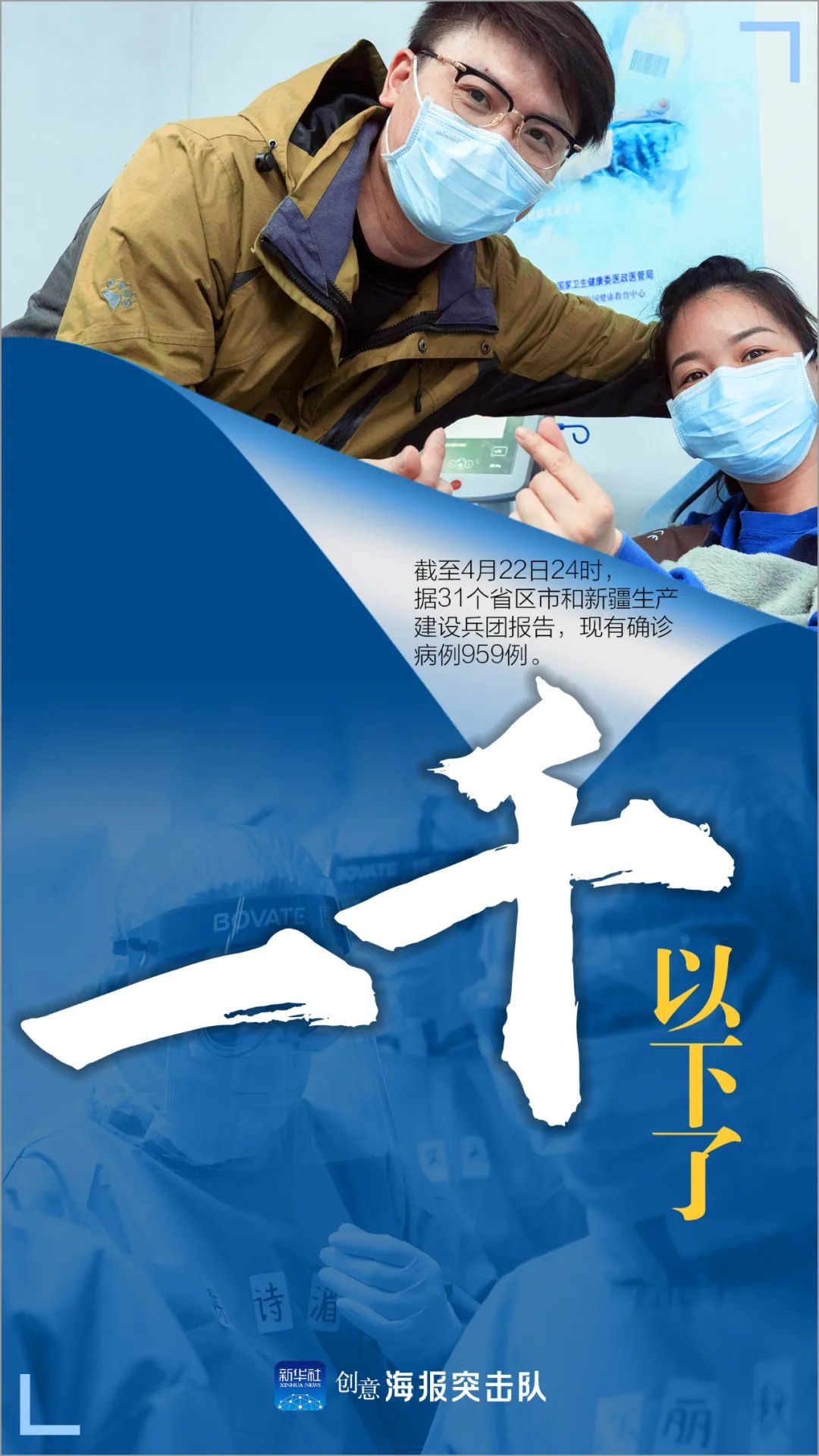
方正清刻本悦宋家族
杨雁
2021年新开发的方正清刻本悦宋有5个不同粗细字重,构成清刻本悦宋家族字体。该字体的设计源于清朝“武英殿”铜活字本《四书章句》。武英殿多以长方宋体字刻印书籍,排印的书籍以书品华贵、版印精良而享誉天下。原帖字形修长,笔画微斜,整齐中平添灵动秀雅之美。方正清刻本悦宋笔画既富含笔墨之意,又彰显刀刻之功,笔刀结合刚柔并济。字里行间隐含着历史古韵,渗透着文化气息,似若点点瑕疵,恰恰给人以质朴自然之美。